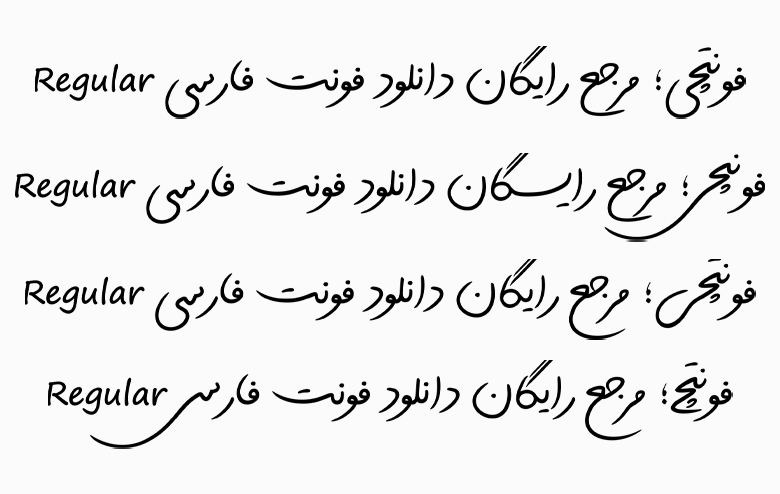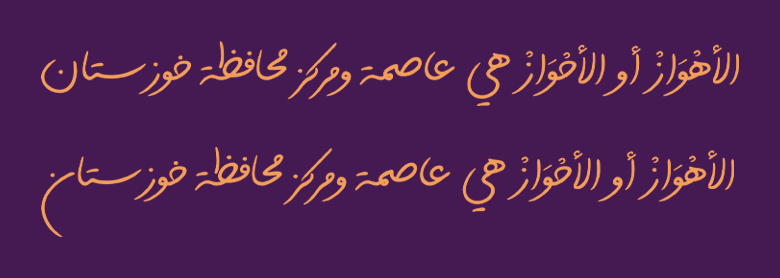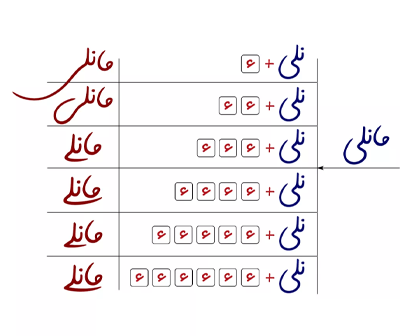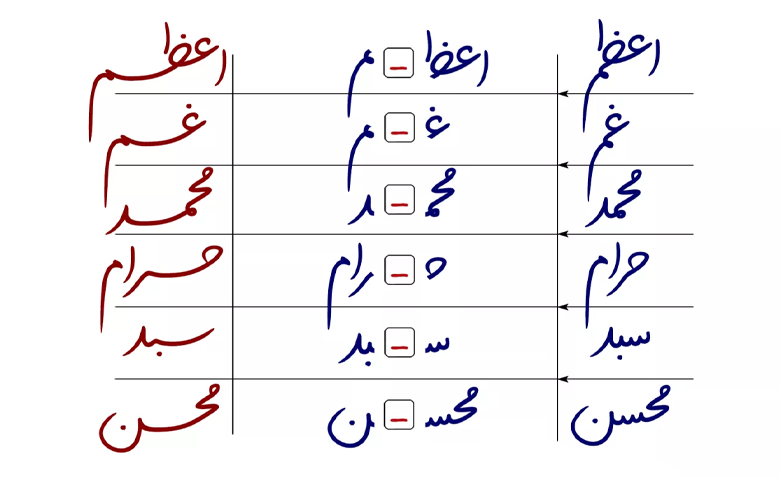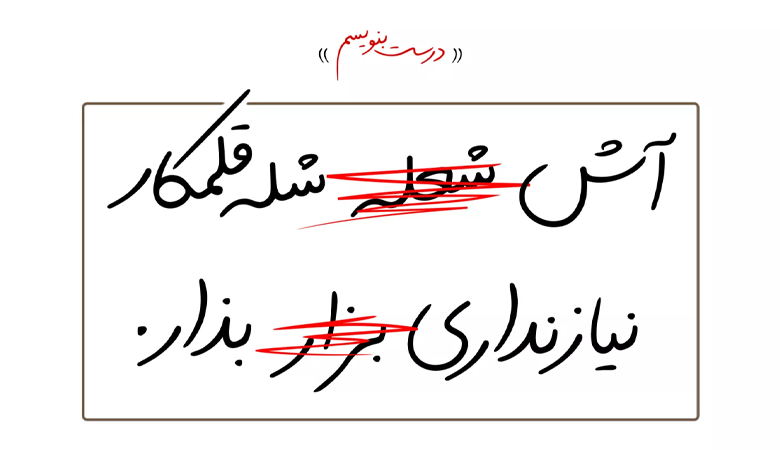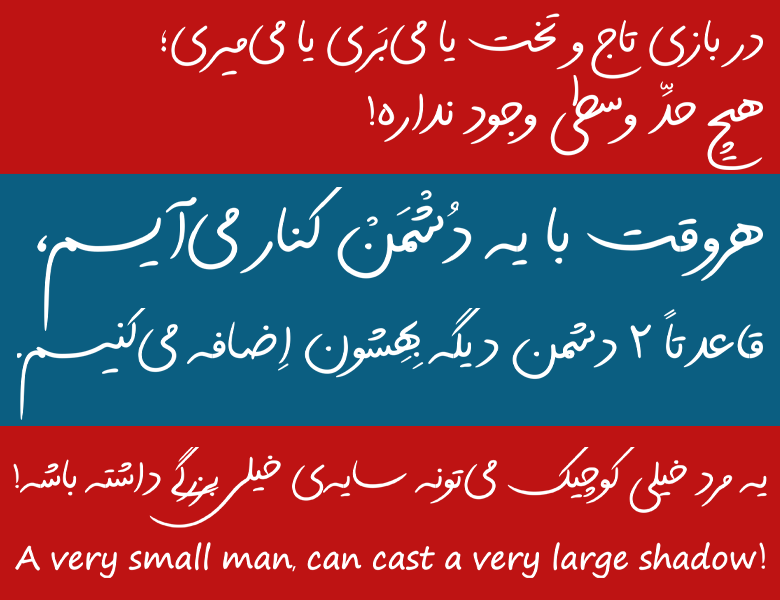
فونت مانلی (Maneli)
فونت مانلی (به انگلیسی: Maneli) یک فونت دست نویس و بسیار نزدیک به دست خط طبیعی است که شاید دستخط شما نیز چیزی مشابه و بسیار نزدیک به این فونت باشد. اما این فونت بر خلاف بسیاری فونتهای دیگر دارای خطوط کرسی سیال است که امکان تایپ کلمات و حروف جایگزین را در چند حالت مختلف به شما خواهد داد. فونت مانلی ۲ ویژگی منحصر بهفرد دارد که اولی تنوع بسیار بالای حروف جایگزین و دیگری امکان خط زدن عبارات است.
محمد عمویی طراح فونت مانلی است که آن را بر اساس خط دست نویس طبیعی و با الهام از روی خط شکسته نستعلیق طراحی کرده است. خطوط در این فونت دارای کشیدگی، منحنی های نرم و شکستگیهای لطیف هستند.
در ادامه این نوشته از سایت فونتچی به نقد و بررسی فونت مانلی خواهیم پرداخت؛ فونتی که به عنوان فونت خودکار میتوانید از آن برای تایپ متن های کوتاه تا بلند استفاده کنید.
معرفی و بررسی فونت مانلی (Maneli)
جدا از کاربردی که فونت مانلی برای تبلیغات، عناوین و متون دارد از آن میتوان به عنوان فونتی برای نامهنگاریهای غیر رسمی استفاده کرد. بسیاری افراد نیاز به تایپ نامههای غیر اداری و غیر رسمی دارند که لزوما باید به صورت دستی تایپ شوند. مانلی به چنین نیازهایی کمک میکند که بتوانید از تایپ خودکار و دست خط طبیعی با استفاده از تایپ ماشین دسترسی داشته باشید.
از دیگر کاربردهای فونت مانلی میتوان به استفاده در جلد کتب و مجلات بهویژه حوزه کودک و نوجوان استفاده کرد. استفاده از این قلم دستنویس برای جلد کتاب میتواند روی جلب توجه بیشتر و همچنین ساختار دوستانهتر کتاب بر اساس موضوع تاثیرگذار باشد.
سبک و وزن فونت مانلی
سبک فونت مانلی دست نویس و در گروه فونتهای مناسب متن و تبلیغات است. از این فونت میتوانید برای متونی که نیاز است ارتباط نزدیکی با کاربر برقرار شود یا درواقع صمیمیت را برقرار کنید استفاده کرد.
در بسته دانلود فونت مانلی TTF یک وزن معمولی Regular قرار دارد. اما در عین حال ترکیبات و حروف جایگزین متعددی دارد که میتواند دست شما را در تایپ حروف و کلمات در شکلهای متنوع زیادی باز بگذارد.
ویژگی و امکانات فونت Maneli
فونت دست نویس مانلی ساختاری بر اساس تایپ با خودکار دارد که بیشتر افراد جامعه معمولا از این نوع نوشتار در دستخط خود استفاده میکنند. بنابراین هرجا نیاز به تایپ یک فونت خودکار و دست نویس داشته باشید، مانلی به شما کمک خواهد کرد.
پشتیبانی از زبان عربی و انگلیسی
فونت مانلی فارسی جدا از این زبان از زبانهای عربی و انگلیسی نیز پشتیبانی میکند. پشتیبانی این فونت دست نویس از هر دو زبان لاتین و خاورمیانهای بهصورت کامل است و شامل اعراب، اعداد و کاراکترهای خاص میشود.
در فونت مانلی تایپ حروف لاتین الهام گرفته شده از چند فونت انگلیسی مختلف است که ساختار نزدیکی را به نسخه فارسی فونت فراهم کرده و صرفا برخی حروف و کاراکترها دارای تغییرات جزئی هستند.
اما در فونت مانلی عربی جدا از اینکه پشتیبانی کاملی از اعراب و حروف بر اساس زبان فارسی وجود دارد، برخی گلیفهای خاص این زبان مثل حروف «ه، ی» که دارای ترکیب دو نقطه هستند نیز پیادهسازی شده تا بهترین خروجی را بر اساس هر زبان داشته باشید.
قراگیری اعراب و کاراکترهای دیگر تزئینی در فونت مانلی عربی نیز استاندارد است و بهگونهای نیست که در صورت همراهی با همزه یا سایر اعراب موجب بههم ریختگی متن یا ایجاد فاصله با کاراکتر قبل یا بعدی شود.
دارای حروف و ترکیبات جایگزین متنوع
فونت جدید مانلی دارای حروف و ترکیبات جایگزین متعددی است که با استفاده از کلیدهای میانبر صفحه کلید میتوانید این ترکیبات را با ظاهری متفاوت تایپ کنید. معروفترین ترکیبی که مشابه هر فونت دست نویس و سنس دیگری در این فونت وجود دارد حرف «ی» و ترکیب «ـی» در آخر کلمات است که کشابه تصویر میتوانید از آن استفاده کنید.
با قرار دادن کاراکتر ء در انتهای حرف «ی»، بسته به تعداد کاراکتر وارد شده مشابه تصویر، میتوانید این حرف را در آخر کلمات با ۶ سبک مختلف تایپ کنید. این ترکیبات خلاقانه بسته به اینکه کلمه مورد نظر در ابتدا، میانه یا انتهای جملات باشند، ظاهر خاصی به متن خواهد داد که توجه بیشتر کاربر را به دلیل ساختار متفاوتش جلب خواهد نمود.
ترکیب جایگزین دیگر فونت مانلی امکان کشیده کردن برخی حروف و ترکیبات است که مشابه تصویر بالا شامل «ـم، ـد، حـ، ـر، ظـ، طـ، ـب، سـ، شـ، ـن» میشود. این ترکیبات کشیده را میتوانید با تایپ کاراکتر ـ همراه با این حروف و ترکیبات استفاده کنید که محدود به این موارد نبوده و بسته به شباهتی که در چندین حرف وجود دارد، دارای تنوع گستردهتری هستند.
فونت دست نویس مانلی با اعداد فارسی
قابلیت دیگر فونت مانلی امکان تایپ گلیف اعداد فارسی و عربی متناسب با این زبان است. کلیه اعداد در فونت عربی مانلی بر اساس صفحه کلید فارسی قابل استفاده هستند. اما جدا از این ساختار، امکان تایپ اعداد «۴۵۶» را به همان ساختار اصلی زبان عربی نیز در اختیار خواهید داشت.
این فونت همچنین برای تایپ عبارت «ریال و تومان» با توجه به اینکه هردو این عبارات دارای امکان استفاده از ترکیبات جایگزین و کشیده هستند، به شما این امکان را خواهند داد تا در طراحی کاتالوگ و بنرهای تبلیغاتی که مبلغ برای محصولات درج میکنید، ظاهر متفاوتی به واحد پولی تومان و ریال بدهید تا بهتر مورد توجه قرار گیرند.
قابلیت خط زدن اشتباهات تایپی
یکی دیگر از ویژگیهای فونت مانلی که در واقع یک خلاقیت در این فونت محسوب میشود، امکان تایپ کلمات به صورت خط خورده است. با استفاده از این ترکیب جایگزین میتوانید برخی کاملت را به صورت خط خورده نمایش دهید که در تولید محتواهایی که جنبه آموزشی برای درست نویسی دارند کاربردی خواهد بود.